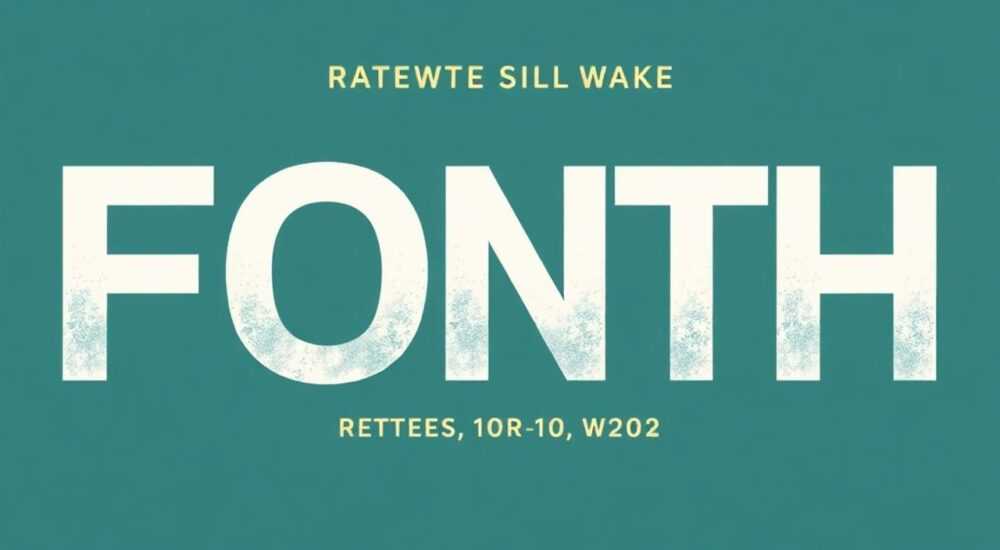
Как сделать свой шрифт в фотошопе
Создание собственного шрифта в Photoshop открывает безграничные возможности для творческого самовыражения и профессионального роста. В современном мире дизайна уникальный почерк становится важным конкурентным преимуществом, позволяя выделиться среди множества стандартных решений. Представьте, что ваш личный стиль буквально воплощается в каждом символе, создавая неповторимую атмосферу бренда или проекта. Однако многие сталкиваются с вопросом: возможно ли создать полноценный шрифт исключительно в Photoshop, не прибегая к сложным специализированным программам?
Основы создания шрифтов в Photoshop
Чтобы начать работу над собственным шрифтом, важно понимать базовые принципы типографики и технические особенности программы. Photoshop предоставляет широкий набор инструментов для создания символов, но требует правильного подхода к организации рабочего процесса. Основными элементами являются размер холста, разрешение (рекомендуется минимум 300 dpi) и система сеток для выравнивания элементов.
- Создайте новый документ с прозрачным фоном
- Настройте направляющие для базовых линий текста
- Используйте слои для каждого элемента символа
Важно помнить о правилах кернинга и интерлиньяжа – расстоянии между символами и строками. Эти параметры существенно влияют на читаемость и эстетику будущего шрифта. Для новичков рекомендуется начинать с базовых глифов (A, E, O, H, N), которые зададут общие пропорции гарнитуры.
Пошаговый процесс создания символов
Начните с создания основных геометрических форм, используя инструмент «Фигура» (U). Для каждой буквы создавайте отдельный слой, что позволит легко корректировать элементы. Работа начинается с определения x-height – высоты строчных букв без выносных элементов. Это ключевой параметр, влияющий на восприятие шрифта.
Элемент |
Размер (%) |
Высота заглавных букв |
100% |
Определяет общий масштаб |
x-height |
50-70% |
Влияет на читаемость |
Длина выносных элементов |
20-30% |
Обеспечивает баланс |
При создании кривых используйте инструмент «Перо» (P) для точного контроля над контурами. Закругления должны быть плавными, без резких изломов. Особое внимание уделите соединительным элементам – серифам, если вы создаете шрифт с засечками.
Сборка и экспорт шрифта
После создания всех необходимых символов переходим к их компоновке. Используйте функцию «Символы» (Window → Symbols) для сохранения каждого глифа как отдельного элемента. Это позволит организовать удобную библиотеку символов. Для дальнейшей работы потребуется специальное программное обеспечение для создания шрифтов, например, Glyphs или FontLab.
- Экспортируйте каждый символ в SVG формат
- Сохраняйте четкую систему именования файлов
- Создайте таблицу символов Unicode
Важно проверить все возможные комбинации букв на предмет корректного кернинга. Специалисты рекомендуют тестировать шрифт на различных устройствах и разрешениях экрана, чтобы обеспечить универсальность использования.
Альтернативные подходы и сравнение методов
Существует несколько способов создания шрифтов, каждый из которых имеет свои преимущества и ограничения. Рассмотрим основные варианты:
Photoshop + Illustrator |
Гибкость векторной графики |
Требует знания двух программ |
FontForge |
Бесплатный инструмент |
Сложный интерфейс |
Glyphs App |
Профессиональные функции |
Платная программа |
Выбор метода зависит от ваших целей и уровня подготовки. Для простых проектов достаточно базового набора инструментов Photoshop, тогда как профессиональные решения требуют более серьезных программных средств.
Экспертное мнение: советы от практикующего дизайнера
Александр Петров, известный типографический дизайнер с 15-летним опытом, основатель студии TypeArt, делится своим опытом: «Когда я только начинал создавать шрифты, совершил множество ошибок. Главная из них – попытка сделать ‘идеальный’ шрифт сразу. На самом деле, это длительный процесс, требующий постоянной доработки и тестирования».
Рекомендации эксперта:
- Начинайте с карандашного наброска
- Создавайте базовый набор символов
- Тестируйте шрифт в реальных условиях
«Особенно важно обращать внимание на межсимвольные пробелы и вертикальный ритм. Даже самый красивый символ теряет свою ценность, если плохо сочетается с другими», – подчеркивает Александр.
Частые вопросы и ответы
Какие основные ошибки допускают новички при создании шрифтов?
- Неправильное соотношение элементов
- Игнорирование системы сеток
- Отсутствие единого стиля
Сколько времени требуется на создание базового шрифта?
В среднем, создание минимального набора символов занимает от 40 до 80 часов, в зависимости от сложности дизайна и опыта дизайнера.
Можно ли использовать Photoshop как единственную программу для создания шрифта?
Технически возможно, но для профессионального результата рекомендуется комбинировать несколько инструментов.
Перспективы развития цифровой типографики
Современные технологии открывают новые горизонты в создании шрифтов. Появление переменных шрифтов (Variable Fonts) позволяет создавать динамические гарнитуры, адаптирующиеся под различные условия отображения. Искусственный интеллект помогает автоматизировать некоторые этапы разработки, но человеческий контроль остается незаменимым.